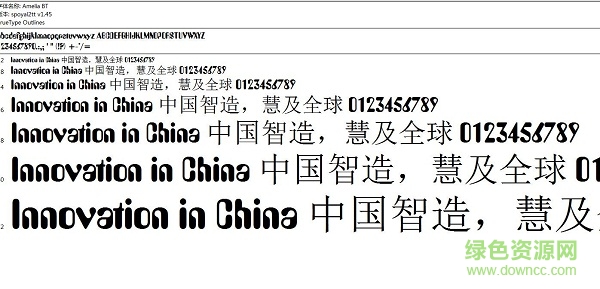
amelia bt字體是一款非常有特點的普通西方字體,字形圓潤,形象生動靈活,黑白對比明顯,字里行間透著幾分風趣,適用于包裝裝飾,平面設(shè)計等方面,歡迎大家免費下載!
amelia bt普通西方體給人的感覺是親切、隨意、可愛,擺脫了一般字體給人的正規(guī)感,適用于兒童類品牌的廣告、產(chǎn)品包裝設(shè)計,以及青春題材的動漫和影視用字。